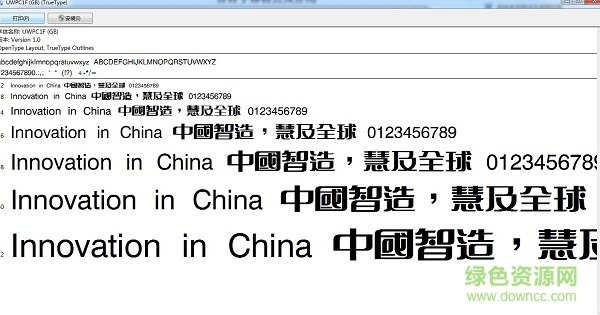
uwpc1f gb regular是一款漂亮的簡(jiǎn)體英文字體,結(jié)構(gòu)合理,線條流暢,粗細(xì)變化自然,整體視覺(jué)效果很棒,適用于廣告制作、包裝設(shè)計(jì)等方面,喜歡這款字體的朋友歡迎免費(fèi)下載!
1.張弛有度,娟秀美觀;
2.極具張力的曲線,加上精準(zhǔn)的幾何線條結(jié)構(gòu);
3.適用于電子書(shū)刊、品牌廣告等領(lǐng)域;